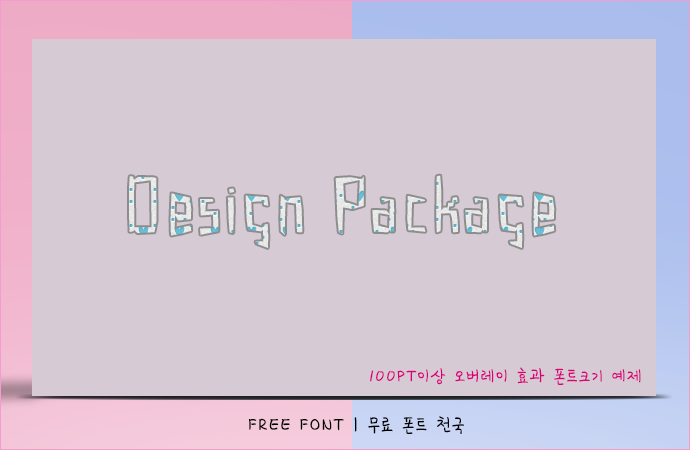
으스스하고 날카로운 Gabardina 영문 폰트
Gabardina 폰트 정보
할로인과 같은 으스스한 분위기에 자주 사용되는 Gabardina 서체입니다. 공포, 귀신, 엽기 등과 같은 호러물 등에 매우잘 어울립니다.
Gabardina 폰트 # 미리보기
Gabardina, 12~80PT 크기로 가독성을 테스트 해본 폰트
Gabardina, 100PT 크기 이상으로 작업한 오버레이 효과를 적용한 폰트
Gabardina, 100PT 크기 이상으로 그레이언트를 효과를 적용한 폰트